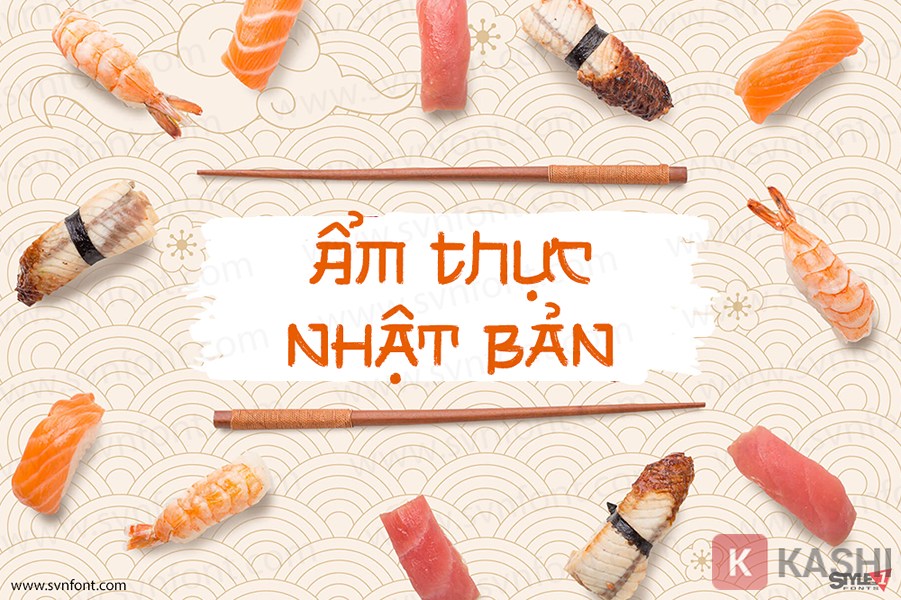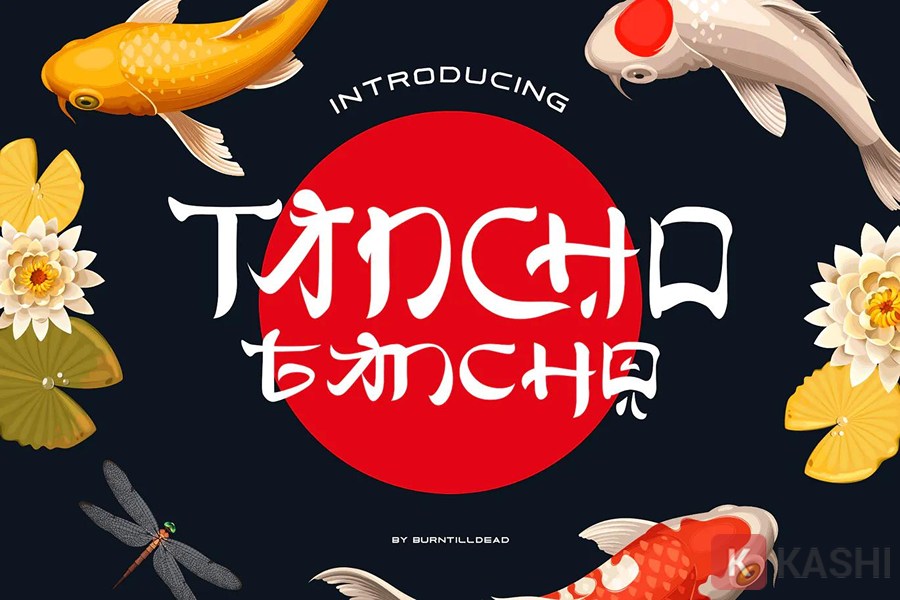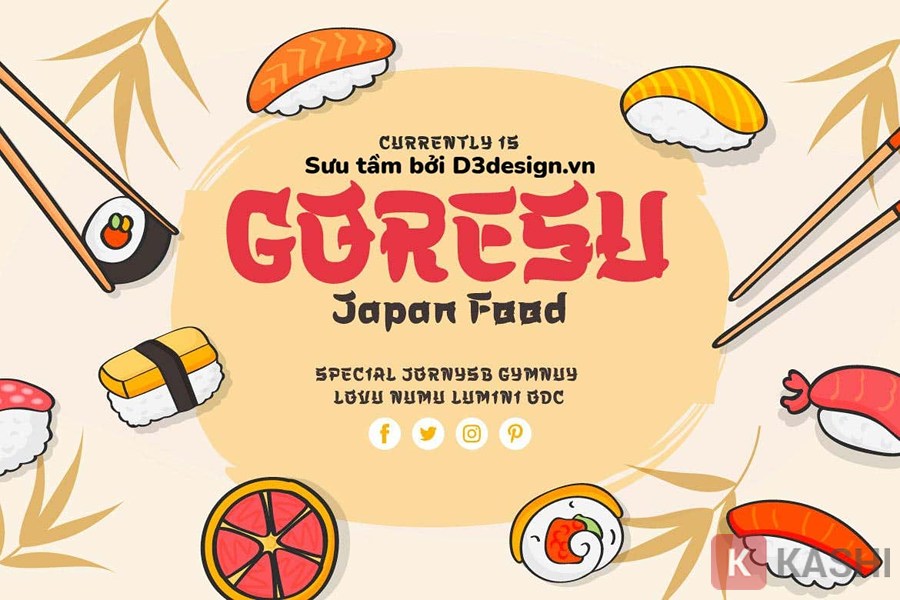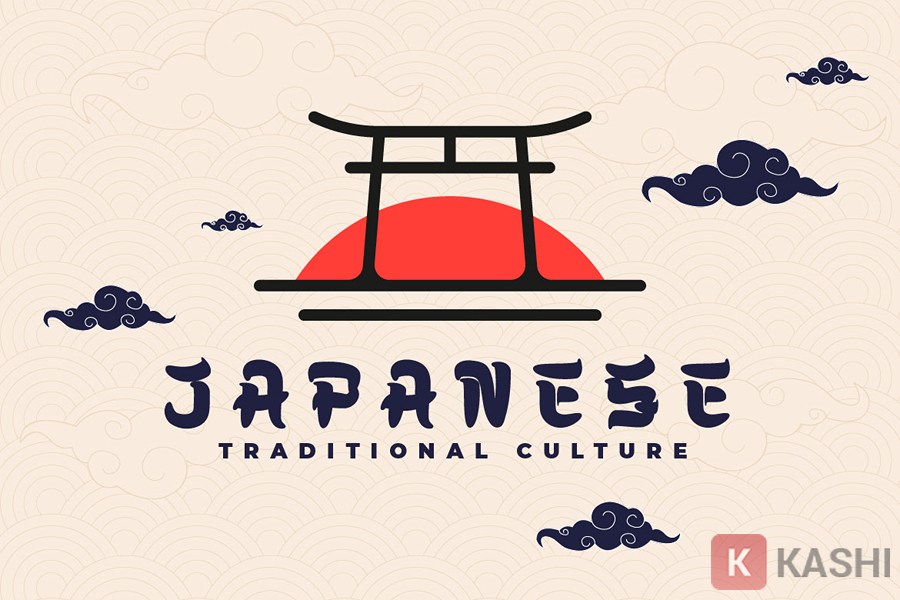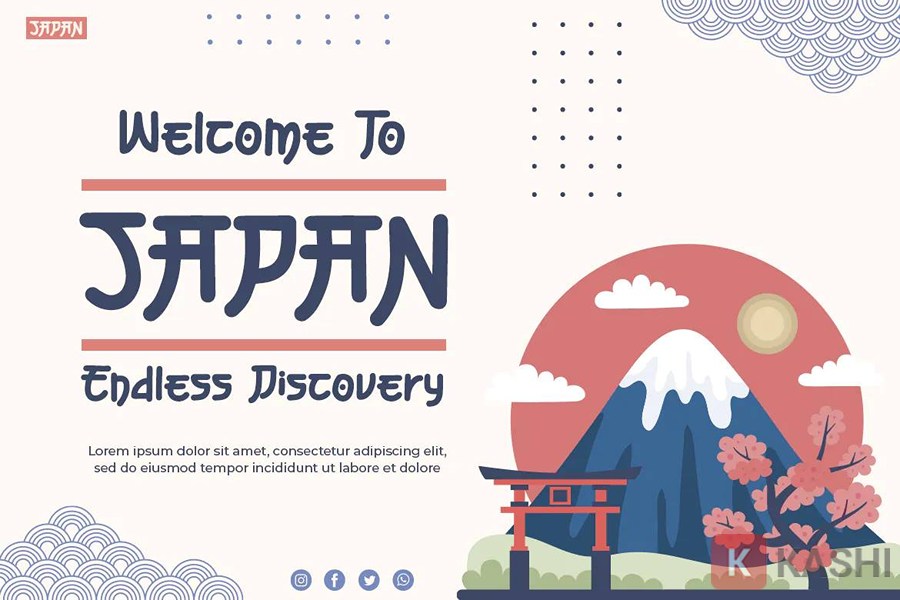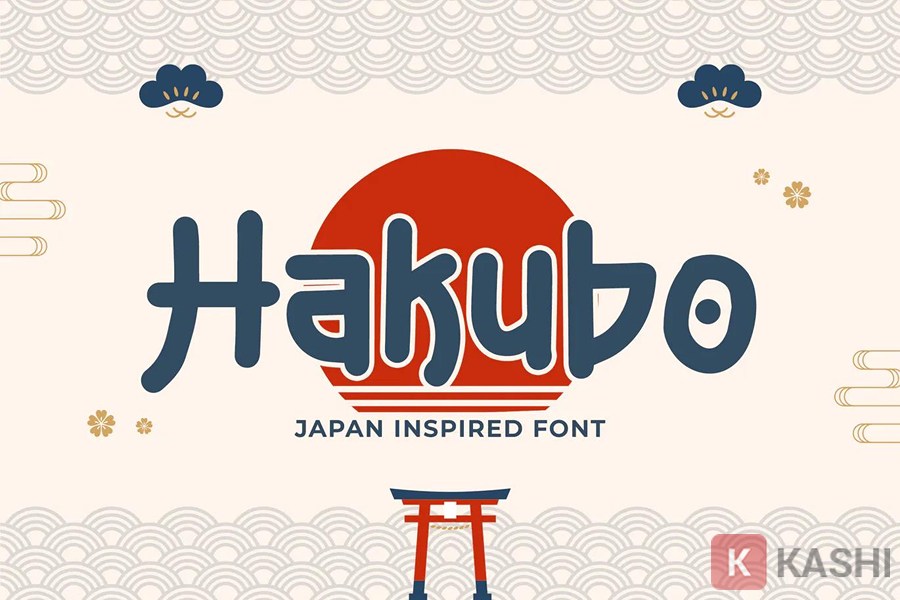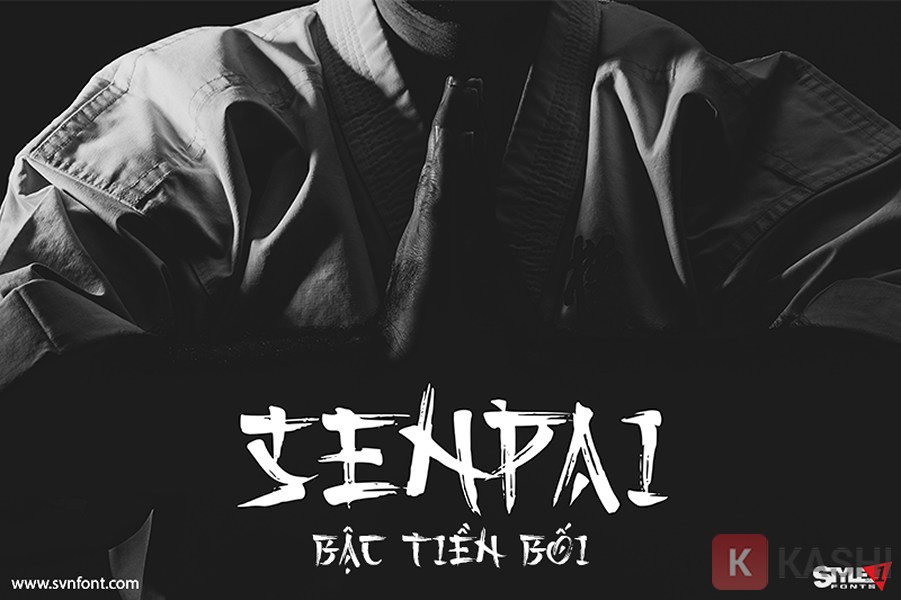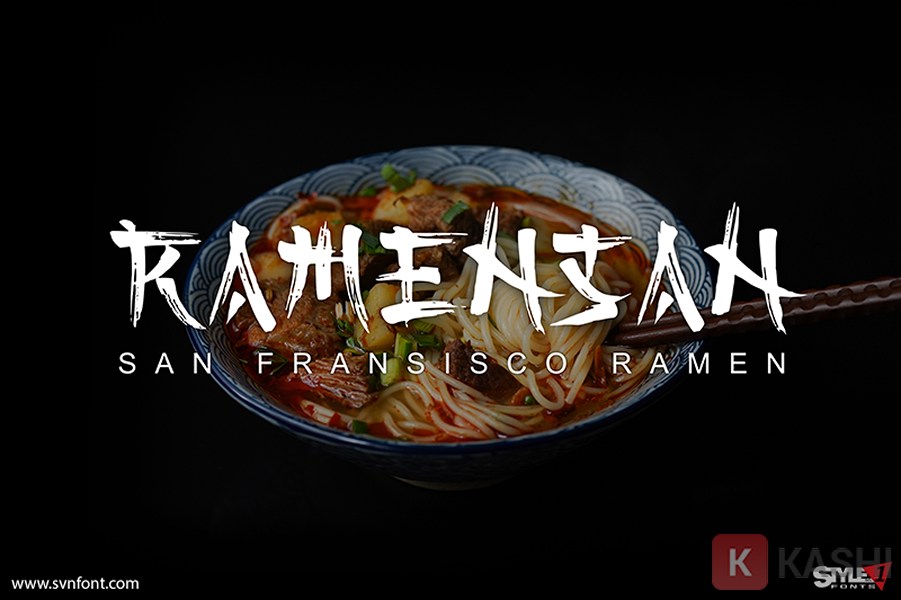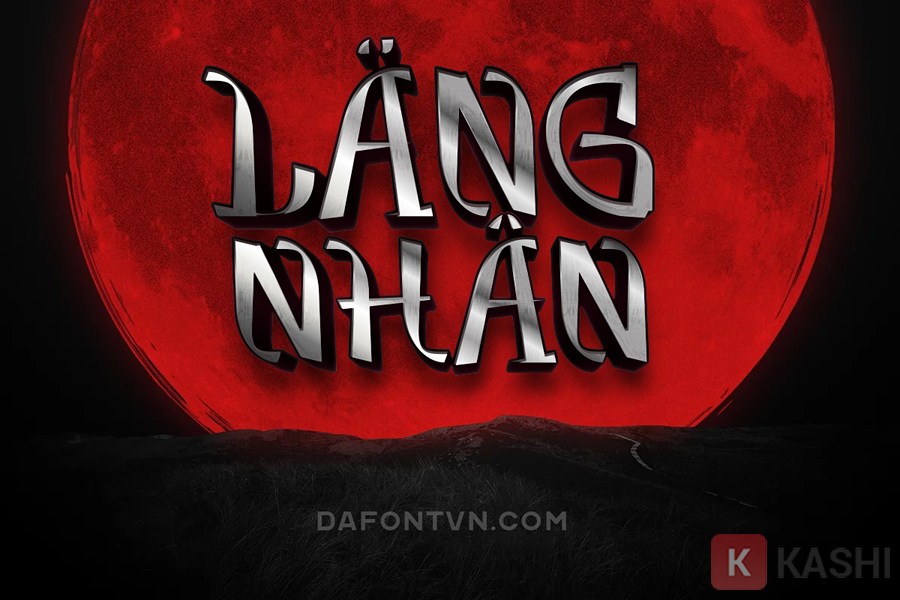
Top 8 Font Chữ Nhật Bản Việt Hóa Đẹp và Độc Đáo Cho Thiết Kế
Font chữ đóng vai trò quan trọng trong việc tạo nên sự thu hút cho văn bản và banner. Tuy nhiên, việc tìm kiếm font chữ tiếng Nhật đã được Việt hóa chất lượng cao khá khó khăn. Bài viết này sẽ giới thiệu đến bạn 8 font chữ Nhật Bản Việt hóa đẹp mắt, độc đáo và miễn phí, hứa hẹn sẽ là nguồn tài nguyên hữu ích cho các dự án thiết kế và in ấn của bạn.
Font Chữ Nhật Bản Việt Hóa Là Gì?
Font chữ Nhật Bản Việt hóa là những font chữ được thiết kế theo phong cách Nhật Bản nhưng đã được chỉnh sửa để hiển thị chính xác tiếng Việt, giúp bạn dễ dàng sử dụng trong các thiết kế.
8 Font Chữ Nhật Bản Việt Hóa Nổi Bật
Dưới đây là 8 font chữ Nhật Bản Việt hóa miễn phí, bạn có thể tải về và sử dụng ngay cho dự án của mình.
1. Font Tokugawa Việt Hóa
Lấy cảm hứng từ nhân vật lịch sử nổi tiếng Tokugawa Leyasu, font Tokugawa mang đậm nét văn hóa Nhật Bản với những đường nét cứng cáp và sắc sảo.
Font Tokugawa
Font Tokugawa Việt hóa
2. Font Kashima
Kashima là font chữ cọ phong cách Nhật Bản, mang lại vẻ đẹp tự nhiên và phù hợp cho nhiều ứng dụng thiết kế như may mặc, xây dựng thương hiệu, logo, tạp chí, banner, quảng cáo,… Font chữ này hỗ trợ in hoa, dấu câu, ký hiệu, số và đa ngôn ngữ.
Font Kashima
Font Kashima cho logo và banner
3. Font Takashimura Việt Hóa
Lấy cảm hứng từ thư pháp Nhật Bản, font Takashimura mang đến sự độc đáo và thú vị cho các thiết kế mang hơi hướng Nhật Bản, Châu Á và phương Đông. Font này dễ dàng sử dụng trong hầu hết các phần mềm thiết kế nhờ hỗ trợ Unicode (PUA).
Font Takashimura
4. Font Hiroo Script Việt Hóa
Hiroo là font chữ hiện đại với phong cách Nhật Bản, mỗi chữ cái được thiết kế tỉ mỉ mang lại vẻ đẹp tự nhiên như chữ viết tay. Phù hợp cho nhiếp ảnh, hình mờ, trích dẫn, tiêu đề blog, áp phích, thiệp cưới, logo, thời trang và nhiều ứng dụng khác.
Font Hiroo Việt Hóa
Font Hiroo
5. Font Shikamaru Việt Hóa
Shikamaru là font chữ kiểu Nhật với nét thô tối giản, lấy cảm hứng từ chữ Kanji. Đây là font in hoa với sự khác biệt rõ ràng giữa chữ hoa và chữ thường, mang lại cảm giác Nhật Bản đặc trưng. Font này phù hợp cho thực phẩm Nhật Bản, hàng hóa, logo, áp phích, phim, game và quần áo.
Font Shikamaru Việt Hóa
Font Shikamaru
6. Font Tancho
Font Tancho mang đậm phong cách Nhật Bản với nét thanh đậm uốn lượn, rất phù hợp cho biển hiệu nhà hàng, đặc biệt là quán ăn phong cách Nhật.
Font Tancho
7. Font Sujoka
Với nét chữ vui tươi, nhí nhảnh, Sujoka là lựa chọn lý tưởng để trang trí banner, quán ăn, logo, quần áo,…
Font Sujoka Việt Hóa
Font Sujoka
8. Font Hakubo
Hakubo là font chữ hiển thị lấy cảm hứng từ Nhật Bản, có khả năng làm nổi bật bất kỳ thiết kế nào. Font này đặc biệt phù hợp cho nhãn hiệu áo phông, bản in hoặc nhà hàng.
Font Hakubo